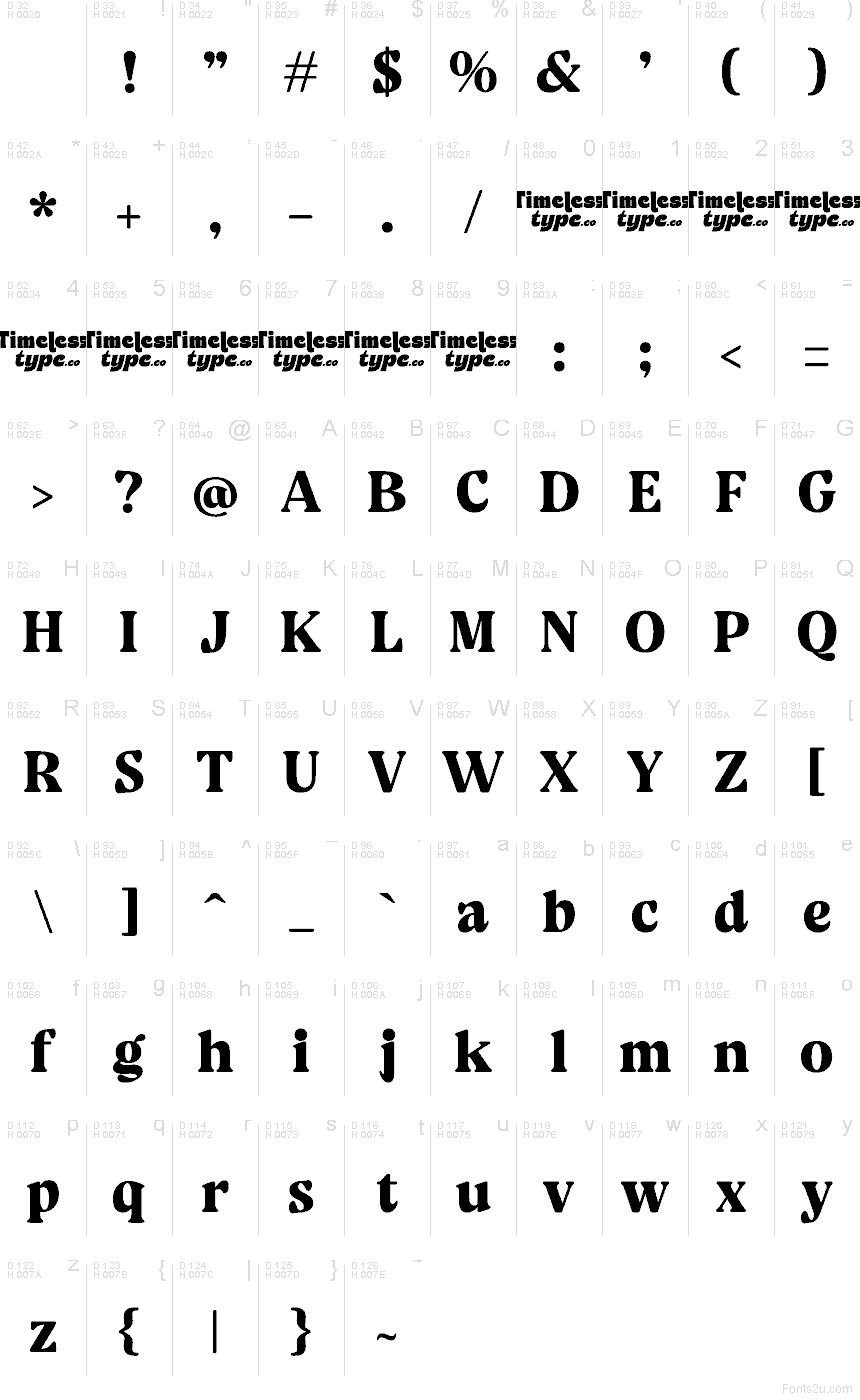
Volkgen Migario von TimelessType.co ist eine kostenlose Soft-Serif-Display-Schrift mit einem Hauch von nostalgischem Storybook-Charakter. Die Buchstaben kombinieren breite, gewichtige Formen mit abgerundeten Ausläufen und tropfenförmigen Endungen, wodurch die Schrift eher warm und theatralisch als streng wirkt.
Sie eignet sich hervorragend für das Branding von Cafés, Flaschenetiketten, Buchcovern, Plakatüberschriften, Verpackungen und Titelkarten – überall dort, wo eine kostenlose Schrift eine literarische Stimmung benötigt, ohne dabei antiquiert zu wirken. Verwenden Sie sie, wenn Wortmarken, kurze Überschriften oder Monogramme ein weiches, leicht dramatisches Flair erhalten sollen, denn die geschwungenen Kurven und gepolsterten Serifen verleihen selbst kurzen Texten eine eindrucksvolle Silhouette.